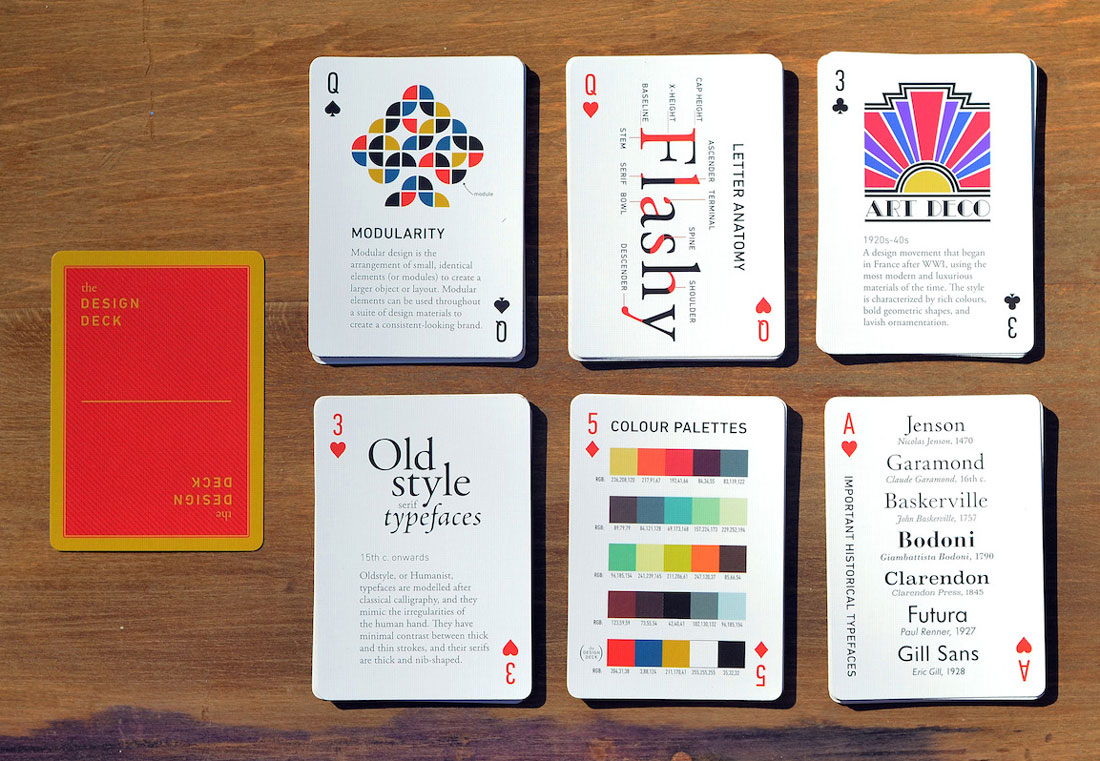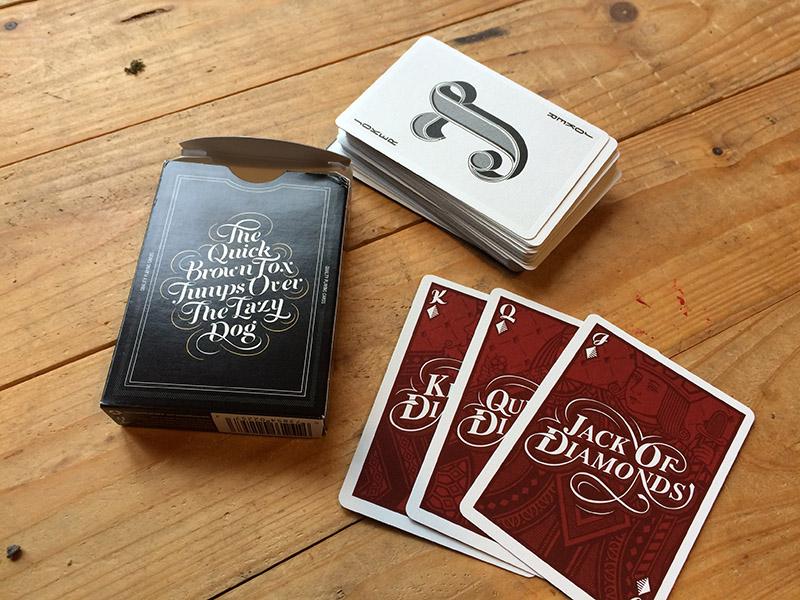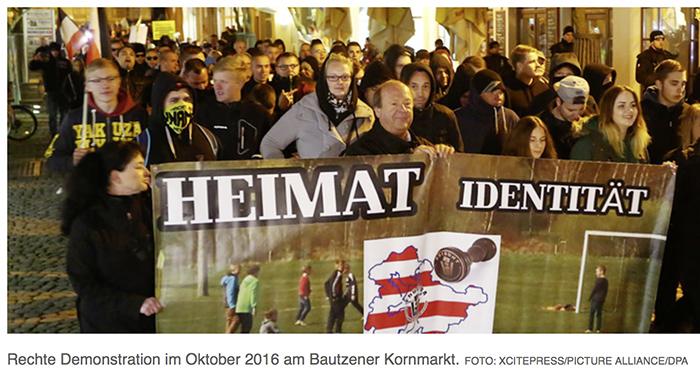
Wenn das Arabische ins Lateinische passt …
So wie die auf den Brettern stehen sind das eh Holländer … :mrgreen:
Gerade von  Mighty Deals im Postfach entdeckt: The Design Deck
Kreatives Unterschneiden bei LA, Baujahr 1961:
Ich finde gerade den Beitrag nicht, aber ich meine hier hatte ich mal einen Hinweis zu der Kickstarter-Kampange für das Type Deck gesehen :-? Das war ca. 2013 oder so ...
Auf jeden Fall ist es jetzt fertig und angekommen:
Facebook ist ja voll von solchen Bildchen und ich frage mich immer, ob die das nicht sehen oder ob es einfach egal ist!? Das sind ja keine Kerningfehler oder so, die nur das geschulte Auge sieht. Oder eine ähnliche Schrift als Zwiebelfisch, so dass man sie nicht leicht entdeckt – nein, es ist immer offensichtlich  :-?:oops:
Es gab halt einfach kein vernünftiges Ä, dass sich für diese Sache hergeben wollte. Das kommt dieser Tage ja öfter vor. ;-)
Ich schätze mal, so etwas entsteht so:
Da ist der euste "Kamerad", der das Transparent entwirft. Dieser nutzt da seine Lieblingsschrift und gibt das fertige "Werk" als offene Datei weiter, an den, der so einen Großformat-Drucker besitzt.
Dieser bekommt beim Öffnen der Datei die Fehlermeldung, dass die verwendete Schriftart nicht installiert sei, also mal schnell die Schrift irgendwo runter laden. Nur bekommt der da eine Uralt-Version der Schriftart. ohne Umlaute, wie man sie Massenhaft auf Freeware- Font- Seiten findet. Jetzt wird kurz vor dem Einsatz das Transparent gedruckt - mit Fallback-Ä. Um das noch mal richtig zu drucken, fehlt dann Zeit und Geld, und lesen kann man es ja auch so...
Nene, mit offenen Dateien und Großformatdrucker hat das wenig zu tun – da muss man die gar nicht in Schutz nehmen. Facebook (und Whatsapp) ist, wie gesagt voll mit diesen Glitter-Wasauchimmer-Sprüche-Bildchen – esoterisch, politisch, kitschig – und immer sind's die äs und üs und ßs, die das nicht mitmachen. Ich habe eher das Gefühl, dass man das eben so hinnimmt und fertig – "ist halt so". Postfaktische Umlaute sozusagen …
Postfaktische Umlaute sozusagen …
Hehe … die als Untypographical Correctness das Pfeifen auf Political Correctness illustrieren,  quasi …
Wenn’s nicht so traurig wäre …
as Ä fühlt sich bestimmt ganz unbehaglich!
*Zensiert* Typophilister! Schon erstaunlich wie das mit der Darstellung schief gehen kann. (Ich habe mal zu eine Anti-PEGIDA-Demo für unsere Volxküche ein Schild „Echte deutsche Kartoffelsuppe“ in deutscher Kurrent geschrieben. Spaß muss sein!) Aber gerade bei der Verwendung der gebrochenen Schriften wird da von einigen Rechten doppelt fehlgegriffen. Falsche Scheibweise mit dem s und ſ sowie Verwendung von englischen Textura wie die Old English. *Grusel* AUSBÜRGERN! ABSCHIEBEN! Oder wenigstens den Frakturführerschein entziehen!
sowie Verwendung von englischen Textura wie die Old English.
Wieso, ist doch totaal richtig! Die deutsche Frakturschrift wurde doch 1941 von den Nazis abgeschafft, und die Führer - ä - Führungsspitze wohnt doch aus rechtlichen Gründen im Land der Old English-Frakturschreiber
Ja sieht denn niemand diese schönen alternativfaktischen Serifen des Ä? Und den alternativfaktischen Strichstärkenkontrast? Mal wieder diese Lügenpresse hier, die das nicht sehen will!!!!11elf
Hach, DIE Geschäftsidee! Eine Sans als alternative factical serifs verkaufen! ;-)
Hehe … statt Serif kommt erstmal Sherrif – diese Woche neu bei Myfonts:
Lft Etica Sheriff
(Companion zur serifenlosen LFT Etica, Publisher: Typetogether)